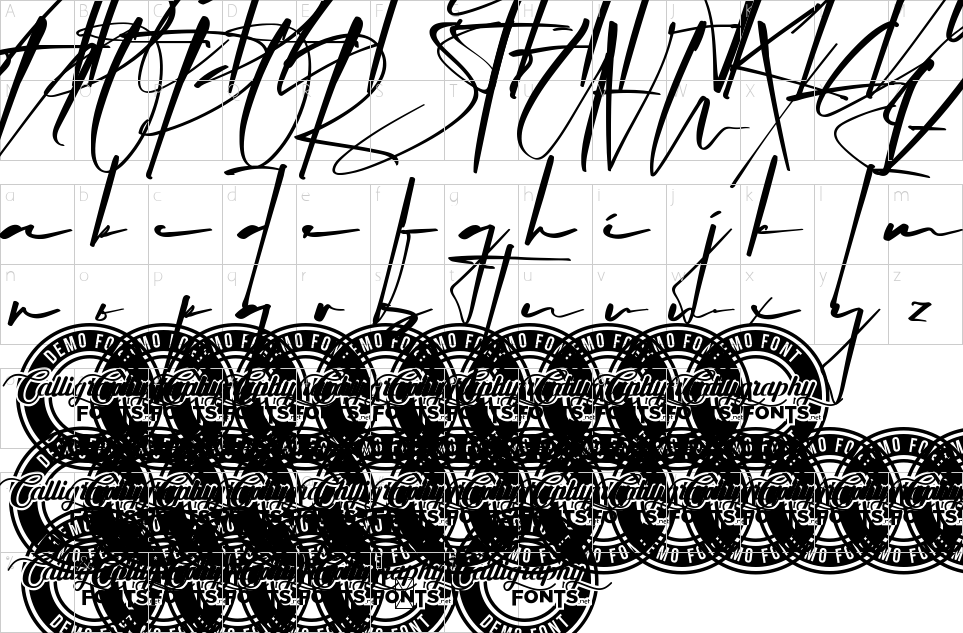
Aqui está uma versão resumida do texto para a descrição da página de download da fonte ‘James Arthur Font’: A elegante e sofisticada ‘James Arthur’ é uma obra-prima criada pelo designer CalligraphyFonts. Esta fonte gráfica, ideal para designers de web ou profissionais digitais, foi projetada com um toque clássico que se adapta bem tanto para websites quanto a impressão digital. Com sua simplicidade e graça em cada letra, ‘James Arthur’ traz uma vibe elegante à qualquer projeto. Possui uma ótima projeção de letras e uma tipografia fluida, tornando-a uma escolha perfeita para títulos destacados ou textos mais delicados. Não apenas designers profissionais apreciam esta fonte, mas também os amantes do design que procuram algo diferente e refinado. Gratuito para download em Windows e Mac, a ‘James Arthur’ é um tesouro entre as fontes gráficas disponíveis gratuitamente na internet. Combinada com seus recursos de tipografia avançados, esta fonte oferece a possibilidade de personalizar seu design com um toque único. Se você está procurando por uma fonte versátil e elegante, ‘James Arthur’ é definitivamente uma opção que merece ser explorada.